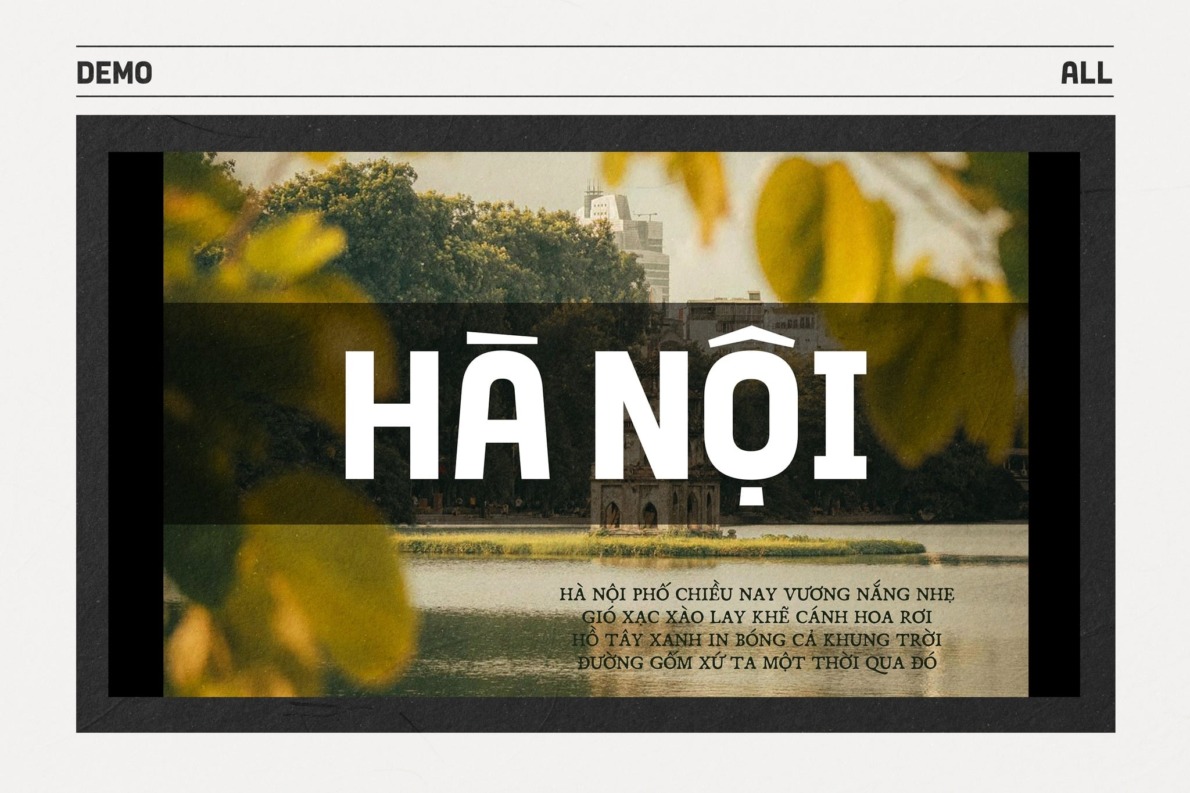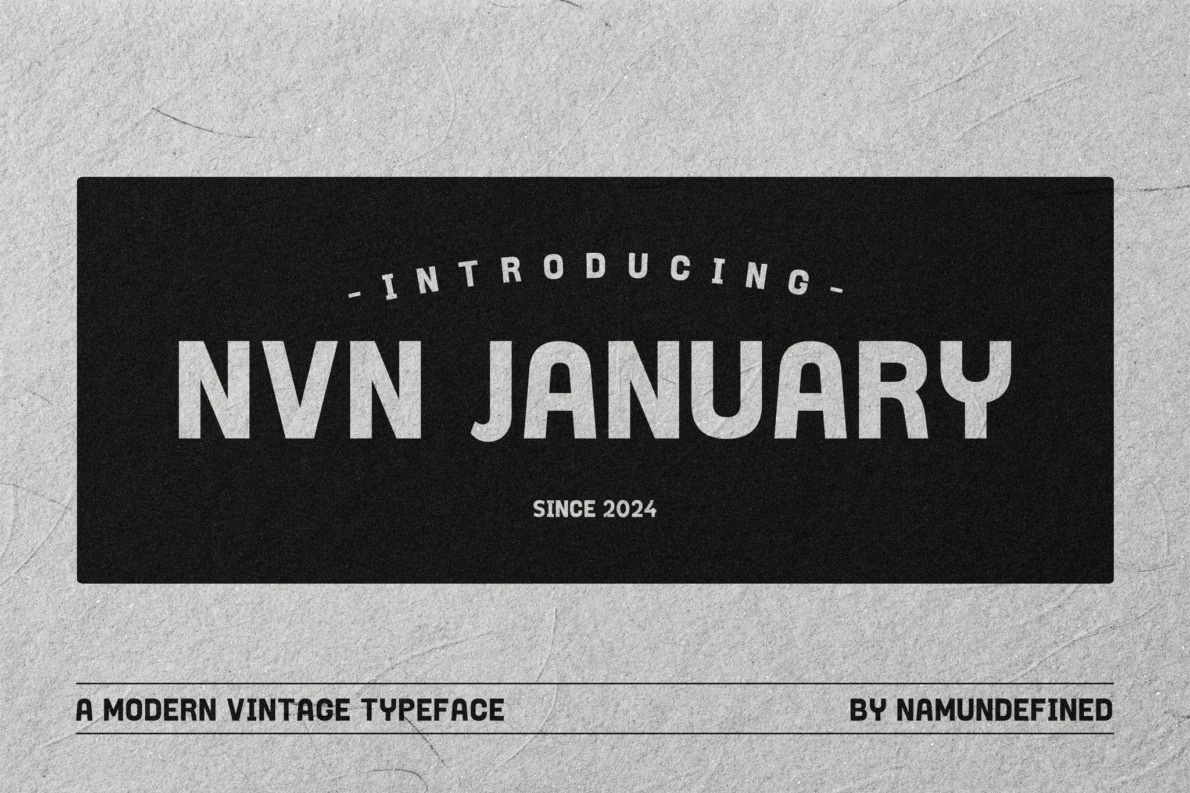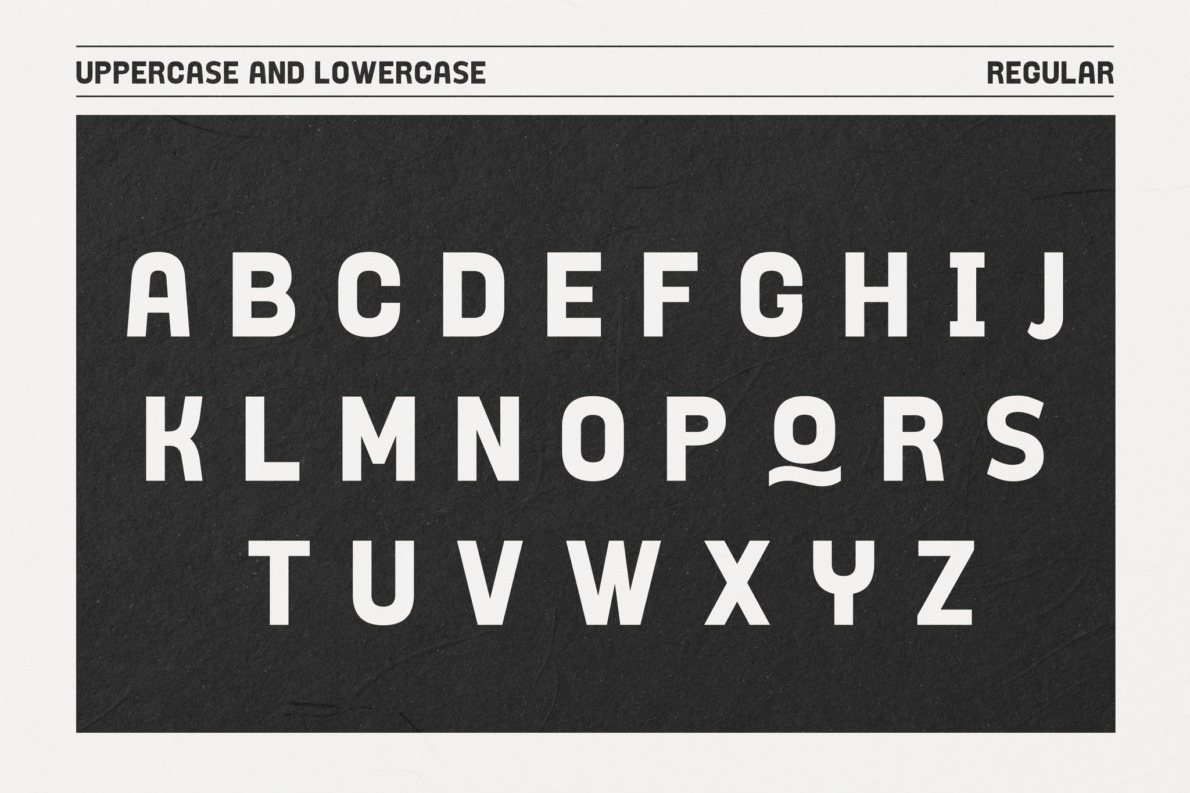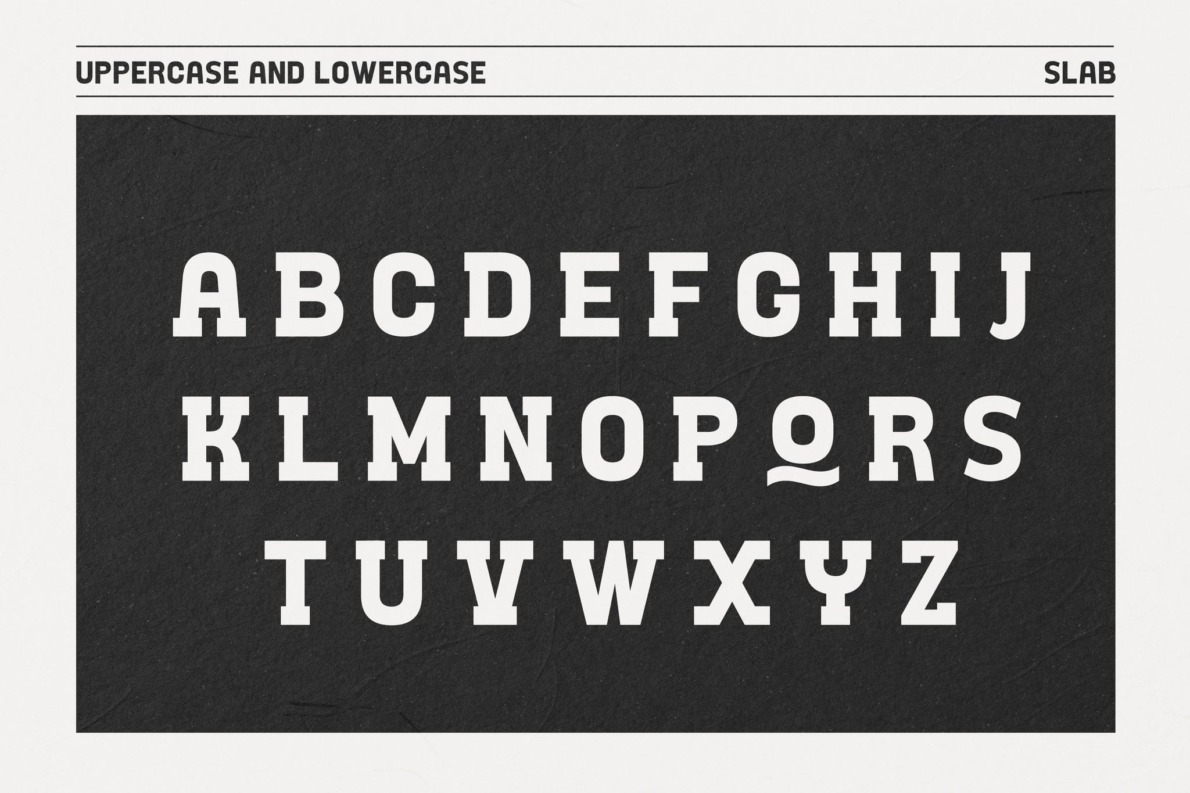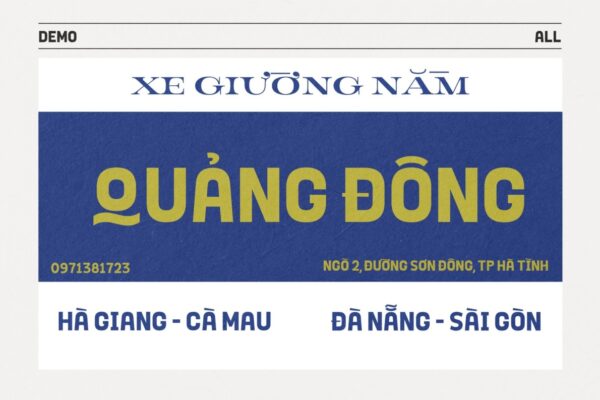
Giới thiệu về Font NVN January
NVN January là một bộ font chữ cực kỳ mạnh mẽ, cứng cáp và đầy ấn tượng, lý tưởng cho mọi thiết kế cần sự nổi bật và chuyên nghiệp. Với ba phiên bản độc đáo: Regular, Slab và Style, bộ font này mang đến sự linh hoạt đáng kinh ngạc, giúp bạn tạo ra những tác phẩm thực sự độc đáo.
1. NVN January Regular
Đây là phiên bản cơ bản, với các nét chữ dứt khoát, gọn gàng và không chân (sans-serif). January Regular mang lại vẻ ngoài hiện đại và tối giản, phù hợp với các thiết kế đòi hỏi sự rõ ràng và trực quan. Font này là lựa chọn hoàn hảo để làm tiêu đề chính, slogan, hoặc các đoạn văn bản ngắn trên poster, banner, và các ấn phẩm truyền thông.
2. NVN January Slab
Phiên bản Slab nổi bật với các nét chữ mạnh mẽ và các “chân” vuông vắn, cứng cáp. January Slab mang lại vẻ ngoài đầy uy quyền và vững chãi, tạo cảm giác đáng tin cậy. Font này rất lý tưởng cho các thiết kế logo, thương hiệu, hoặc các ấn phẩm in ấn cần sự mạnh mẽ, như báo cáo, catalogue, và danh thiếp.
3. NVN January Style
Phiên bản Style là điểm nhấn đặc biệt của bộ font này. January Style sử dụng các nét chữ được cách điệu độc đáo, mang đến một vẻ ngoài sáng tạo và đầy cá tính. Font này phù hợp để tạo các tiêu đề phụ, trích dẫn, hoặc những dòng chữ cần sự phá cách, giúp tác phẩm của bạn trở nên cuốn hút và khác biệt.
Với ba phiên bản linh hoạt, NVN January là một công cụ mạnh mẽ trong tay các nhà thiết kế. Bạn có thể dễ dàng kết hợp cả ba font để tạo ra một bố cục hoàn hảo, vừa mạnh mẽ, vừa chuyên nghiệp mà vẫn đầy tính thẩm mỹ.